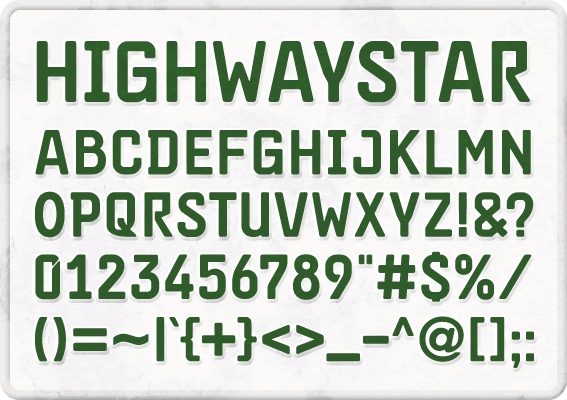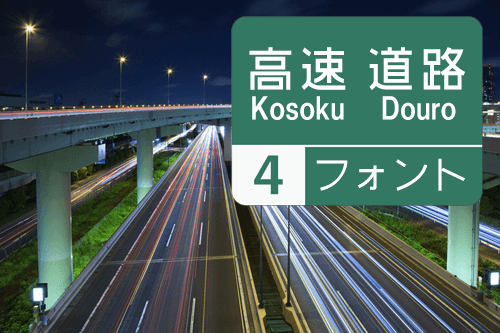
道路標識の文字も再現できる高速道路フォントまとめ
高速道路の標識を再現したい場合に使える高速道路フォントをまとめてみました。標識という性質上、視認性がよく見やすいフォントになっています。道路関係のデザインをするときなどに紹介したフォントを試してみましょう。
GD-高速道路ゴシックJA
高速道路標識の文字に採用されている書体である道路公団標準文字を再現したフリーゴシック体。漢字はJIS第一水準を中心として収録しています。
トラフィックサインJPN
文字を入力すると道路標識を表現できるフォント。日本国内で使われている標識を収録しています。
トラフィックサインWLD
文字を入力すると道路標識を表現できるフォント。こちらは海外で使われている標識を収録しています。
ハイウェイスター
視認性が高い欧文フォント。道路標識はもちろんのこと、クルマのナンバープレートを表現するときにも使えそうです。